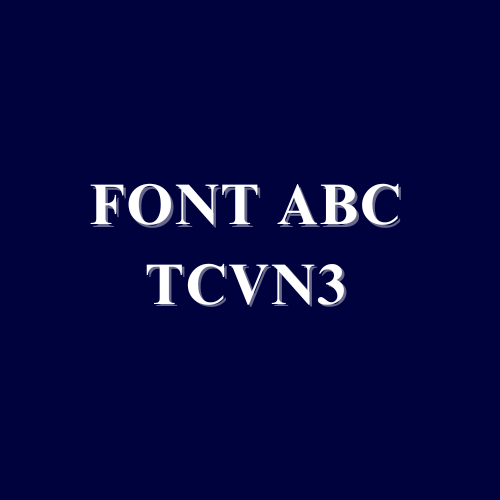
Phân loại: Đơn giản
Font ABC (còn được gọi là Font TCVN3) là phông chữ truyền thống thuộc bộ font chữ việt hóa, được sử dụng rộng rãi tại Việt Nam. Bộ Font ABC này, hỗ trợ gõ tiếng Việt với dấu tiếng Việt đầy đủ, cho phép người dùng tạo và đọc các tài liệu tiếng Việt một cách chính xác. Ngoài ra, bộ Font ABC còn cung cấp nhiều kiểu chữ đẹp, đa dạng, phù hợp cho việc tạo các tài liệu văn bản, thiết kế, và in ấn với phong cách truyền thống. Với đa dạng các kiểu chữ đẹp mắt và dễ đọc, bộ font này đã trở thành lựa chọn hàng đầu cho nhiều người dùng khi soạn thảo các tài liệu bằng tiếng Việt.